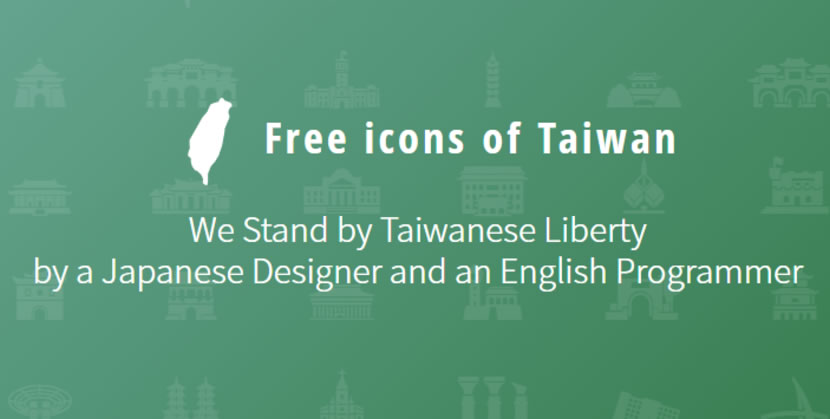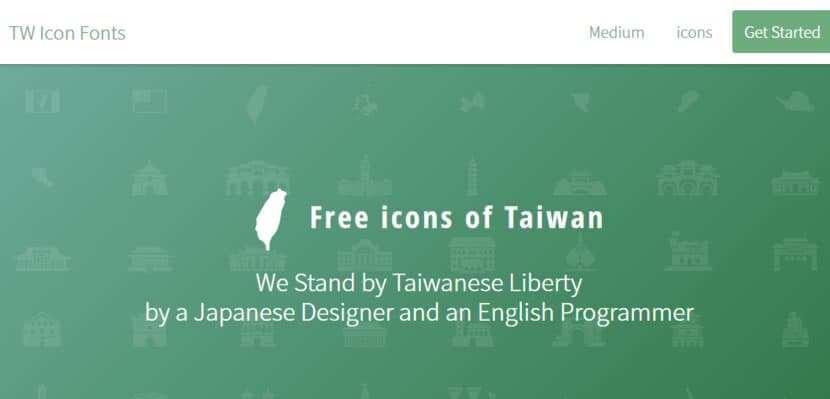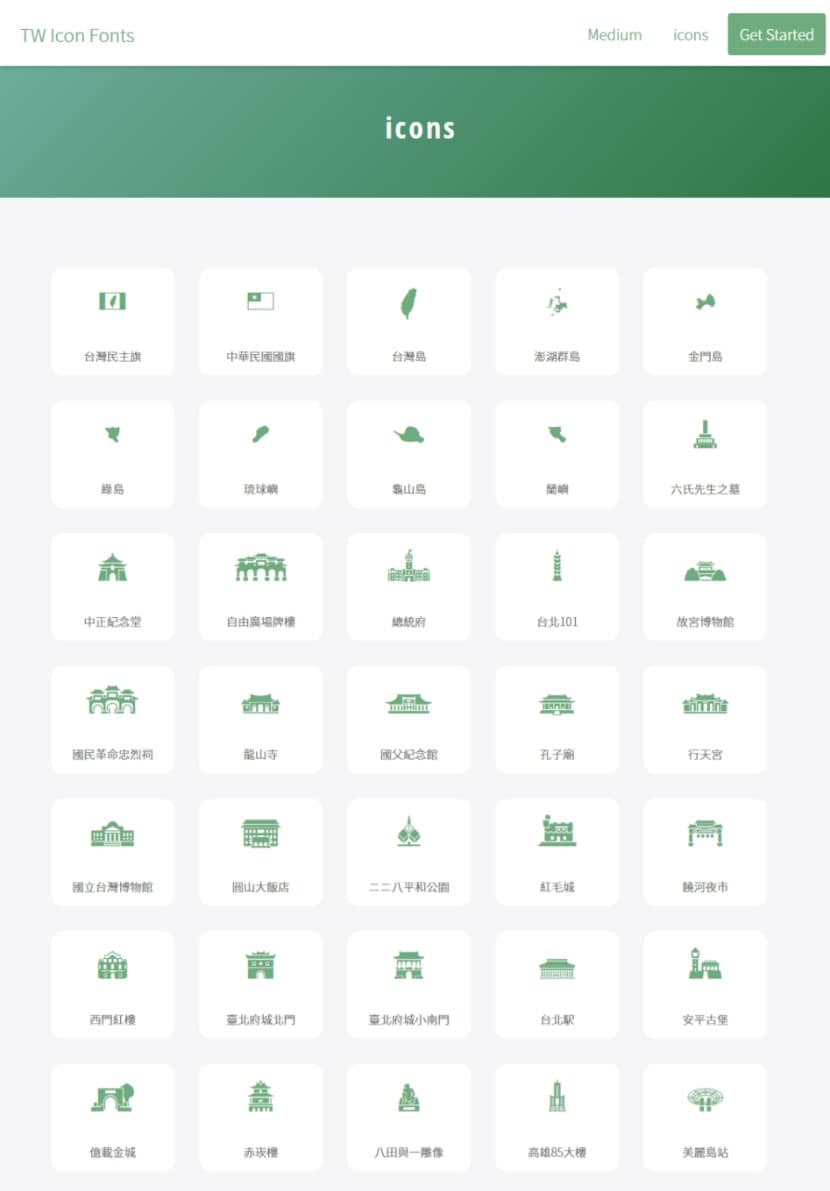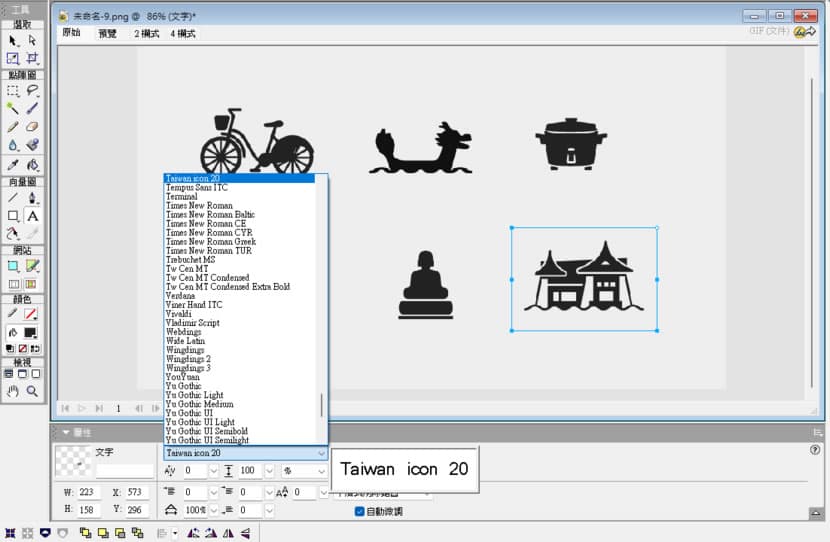
每個人對台灣的印象各不相同。從外國人的角度審視台灣的社會與旅遊面向,夜市熱鬧的人聲、阿里山的壯麗日出、日月潭的湖光山色、太魯閣的峽谷奇景,往往構成他們對台灣的第一印象。然而,當外國友人在台灣稍作停留,深入體驗在地生活後,便會發現更多台灣獨有的魅力:完善的全民健保制度、隨處可見的 YouBike 共享單車系統等。要在文案或網站中精準表達這些豐富多元的台灣元素並非易事,所幸,Taiwan Icon Font 這套圖示字型為我們提供了絕佳的解決方案。
跨國合作的設計成果:在地特色與國際視野的完美結合
Taiwan Icon Font 是一套充滿台灣在地特色的免費圖示字型,由居住在台南的日本設計師 holoko 與旅居台灣的英國程式設計師 Rob 攜手開發。這個跨國合作的設計團隊,以「台灣旅遊」為創作主軸,精心設計出眾多台灣旅遊景點的專屬圖示。其涵蓋範圍廣泛,不僅包含台灣著名地標如台北 101、中正紀念堂,更融入了深具台灣文化特色的元素,如香醇的珍珠奶茶、經典的台灣啤酒,以及便民的捷運系統和 YouBike 共享單車等,完整呈現台灣從觀光到生活的多元面貌。
想要在文案或網頁中,表達含有台灣特色的意象元素,Taiwan Icon Font 是個簡單且有效的方案。